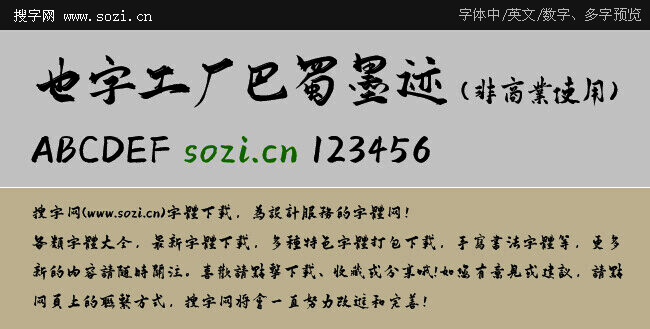
也字工厂巴蜀墨迹
搜字网给大家提供一款也字工厂巴蜀墨迹(非商业使用)中文字体下载,也字工厂巴蜀墨迹是一款书法字体,全套字体采用繁体进行设计,最大程度保留了字体中笔墨书写的痕迹,还原了书法字体该有的本真质感。适合应用于海报设计、包装设计、网页设计等应用(此字体为个人非商用版,商用可以联系:官方网址:https://yefont.com/home,联系方式:13798980448)。